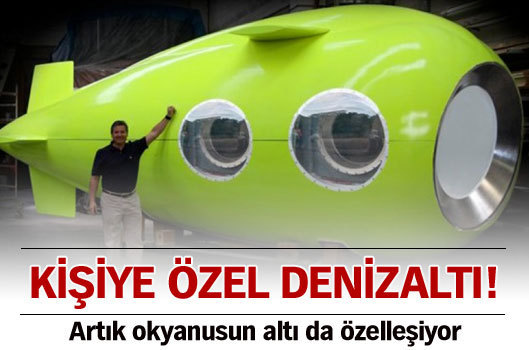
Habertürk'deki font ?
Bu fontun ismi nedir?
Myriad Pro Falandır Heralde Emin Diğilim Ama.
Akzidenz Grotesk büyük ihtimal gazetelerde en yaygın font çünkü çok geniş bir aileye sahip http://en.wikipedia.org/wiki/Akzidenz-Grotesk
Century gothic fontunda yazıcaksınız yazınızı sonra o yazıya photoshopta stroke ve inner shadow uygulayın aynısını çıkartabilirsiniz
Akzidenz Grotesk, Franklin Gothic.